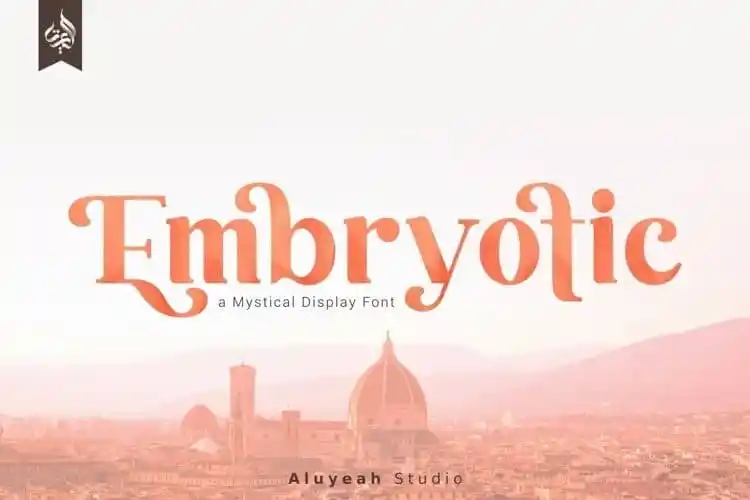
Embryotic Serif é uma fonte serif moderna que traz a surpresa de alternativas únicas e ligaturas para dar vida ao texto. Desenvolvida cuidadosamente pela 99designs, essa font se destaca não apenas por seu estilo simples e elegante, mas também por suas características inovadoras como alternâncias estilísticas e ligaturas. Essas opções de tipografia abrangem uma ampla gama de recursos OpenType que criam um olhar luxuoso em qualquer design. Inspirada nas marcas top do mundo, essa font permite que designers apresentem projetos com um toque sofisticado e elegante, tornando-a uma escolha perfeita para ambientes onde a sofisticação é requisito. Sua complexidade de ligação única e sua paleta de alternâncias estilísticas criam uma textura única que permite personalizar os elementos do layout conforme necessário. Seja em um projeto editorial ou em um site profissional, Embryotic Serif atinge o nível de sofisticação necessária para destacar qualquer design.